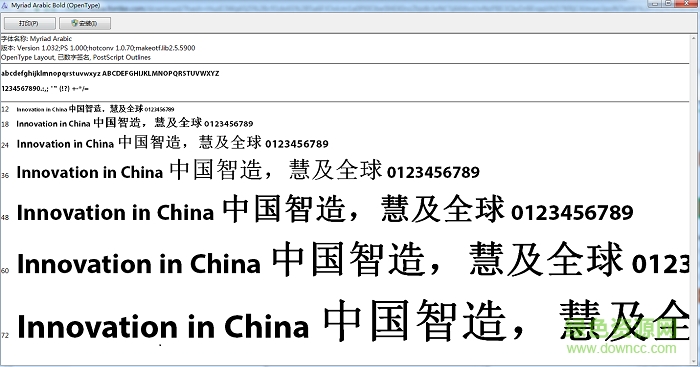
myriad arabic bold-粗體
myriad arabic字體是一款表現(xiàn)力強的粗體字體,和一般的無襯線字體相比,myriad的筆畫粗細變化更明顯,本站為大家免費提供myriad arabic regular和myriad arabic bold兩款字體,需要的朋友快來下載吧!
Myriad字體介紹
Myriad是一種西文無襯線字體,屬于人文主義體,是由羅伯特·斯林巴赫(Robert Slimbach,1956年-)和卡羅·圖溫布利(Carol Twombly,1959年-)在1990年到1992年左右以Frutiger字體為藍本為Adobe公司設(shè)計的。
myriad arabic-粗體